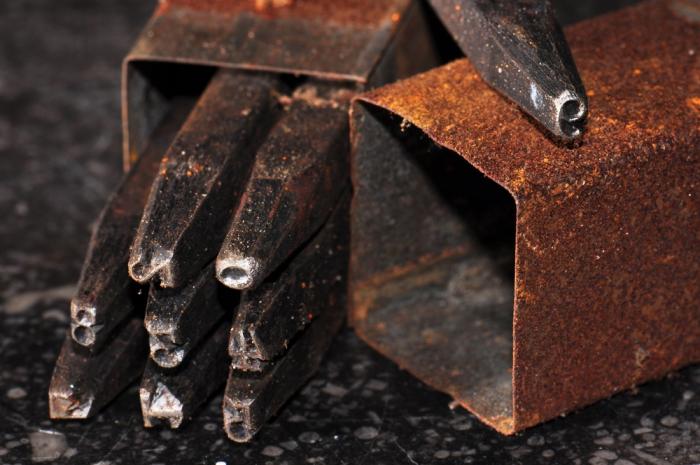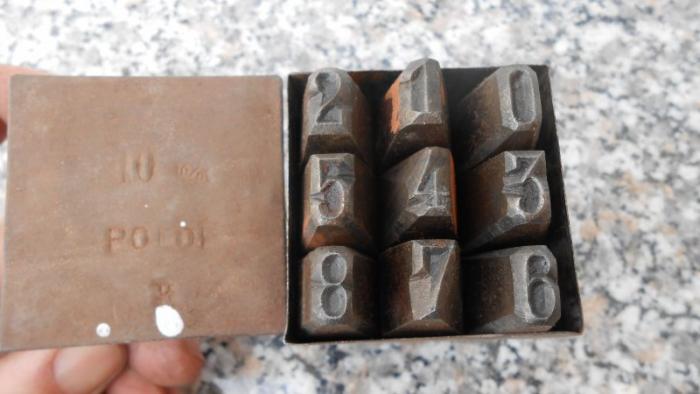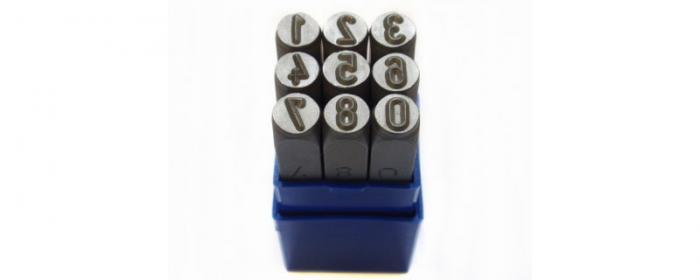
Zahlen-Schrift gesucht
ich kann leider keinerlei Info beifügen außer die Grafik anzuhängen, würde mich jedoch sehr freuen, wenn mir hier jemand helfen könnte!
Schlagzahlen?
Diese wurden von den Herstellern als "schliche Ziffern" speziellhierfür gestsaltet, bei jedem Hersteller vetwas anders, und ähnelten DIN1451 / DIN 17 schon, ohne sich direkt hierauf zu stützen. Eine digitale Schrift hierzu gint es eher nicht, ist auch eine ganz andere Beschiftungs-technik, und ein ähnliches Problem wie Gravierschablonen.
Danke snowscreen, die ist es leider nicht, weder in der alten, noch der neuen Form.
Danke catfonts, damit könntest du Recht haben, "deine" Schlagzahlen sehen jedoch (grade die 4) wieder anders und mehr nach der DIN-Schrift aus.
Falls es wirklich keine digitale Schrift gibt, muss ich die halt nachstellen.
War ja nur eine mehr oder weniger zufällige Zusammenstellung verschieden alter Schlagzahlen, unterschiedlicher Hersteller, um zu zeigen, das es hier so gut wie keine Norm gibt, jeder vhersteller hat bsich seine Ziffern und Buchstaben selbst entworfen